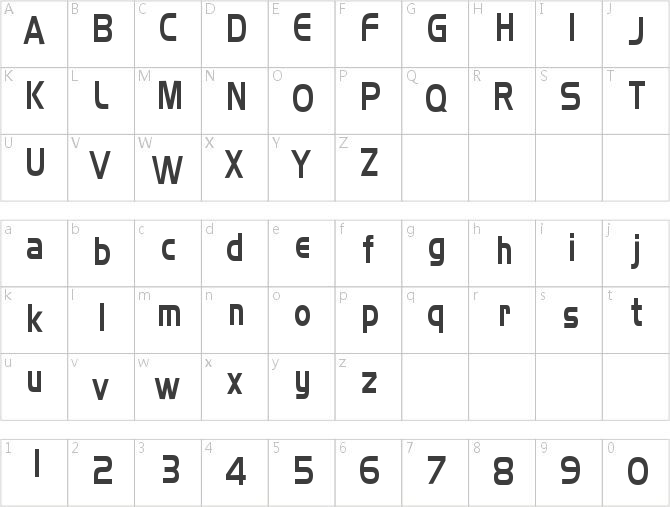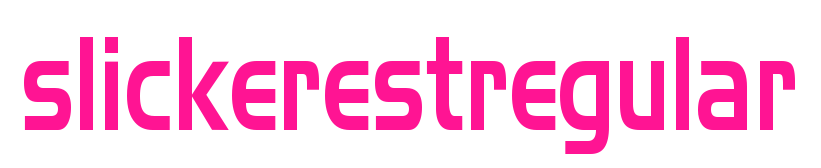
slickerestregular 詳情頁(yè)
slickerestregular字體字庫(kù)是一款讓人賞心悅目、百看不厭的英文字體,適合各類廣告和產(chǎn)品包裝設(shè)計(jì)應(yīng)用,字體大小0.04MB,格式為ttf字體,上傳用戶是gagilang,作者/版權(quán)方為未知